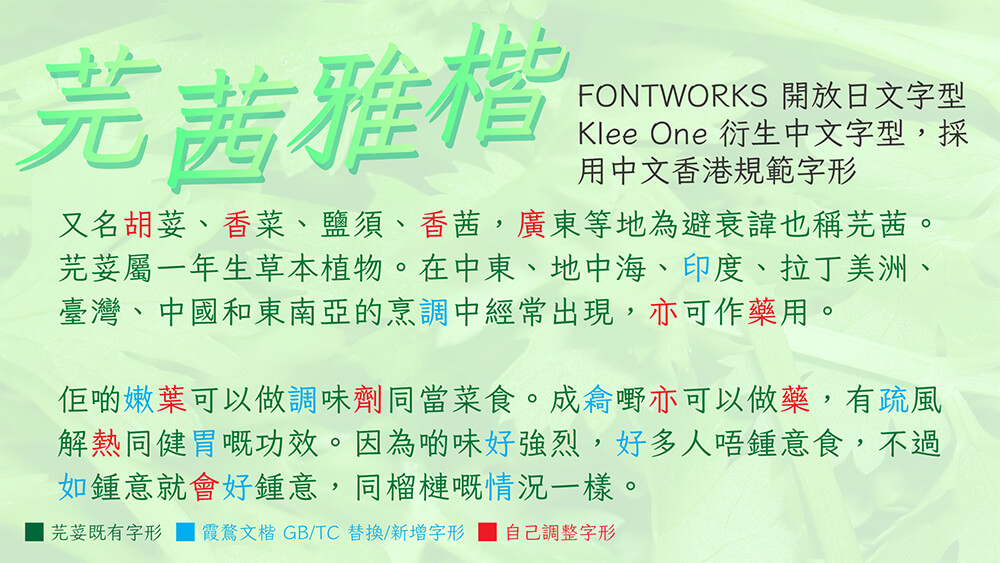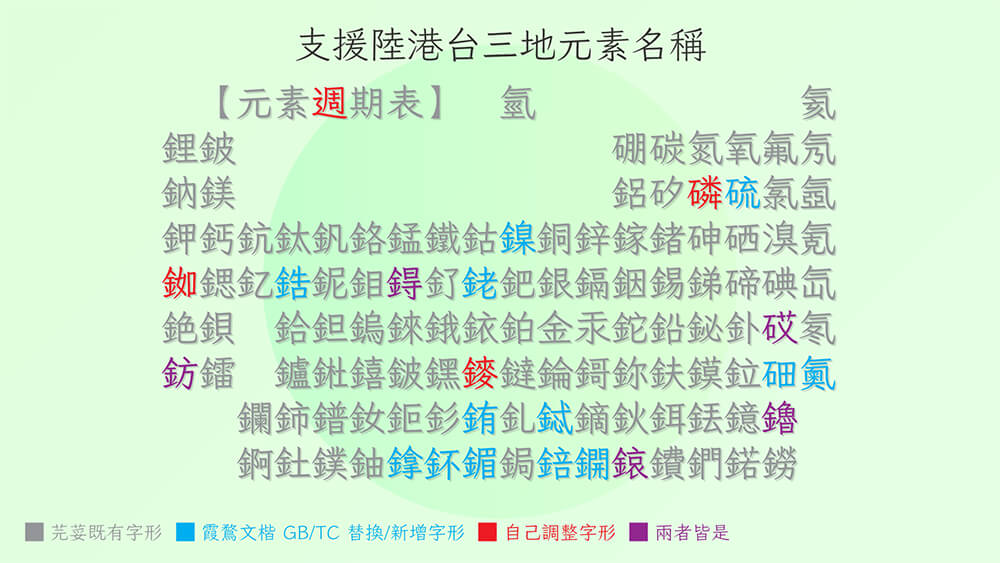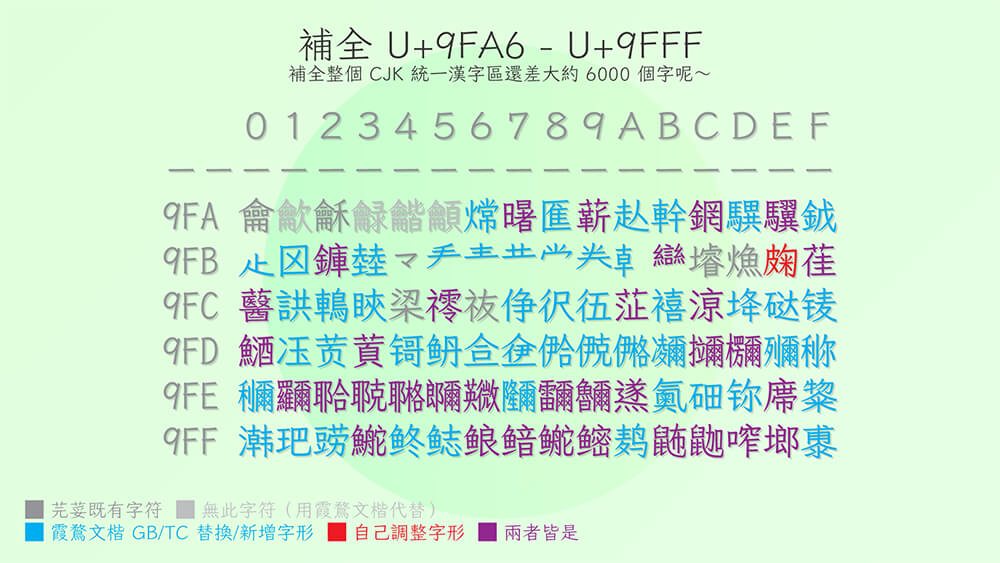
芫茜雅楷Regular
字体风格: 楷书
本字型在芫荽的基础上,加入霞鹜文楷 GB 和 霞鹜文楷 TC 所收录的汉字,并且尽可能调整字形贴近香港字型标准,总字数(汉字)高达约 15 000 个,适合任何学科领域的香港课本使用。
注意 1:現在仍未完全調整來自霞鶩文楷 TC 的字形!
字數
(包括基本區和擴展區字符,不包括兼容區字符)
• Klee One:8000
• 霞鶩文楷 GB:8267
• 芫荽:9778
• 芫茜雅楷:15 270
• 霞鶩文楷 TC:15 277
• 霞鶩文楷:22 270
字形風格
• Klee One:日本標準
• 霞鶩文楷 GB:國家(大陸)標準
• 芫荽:台灣標準
• 芫茜雅楷:香港標準
• 霞鶩文楷 TC:傳承字形
• 霞鶩文楷:雜糅國家標準和日本標準
芫茜雅楷Regular”是一款书写很新颖的字体,字体大方,适合各种设计作品使用!欢迎下载!